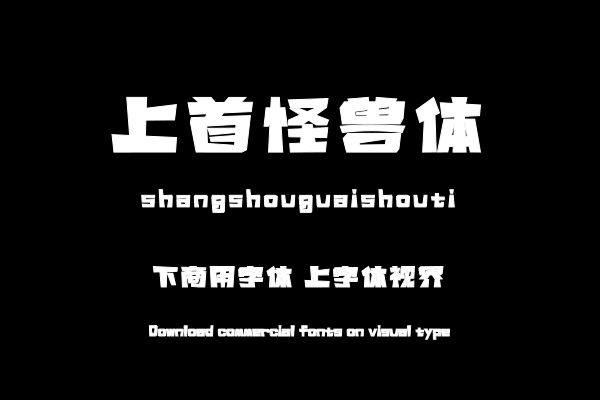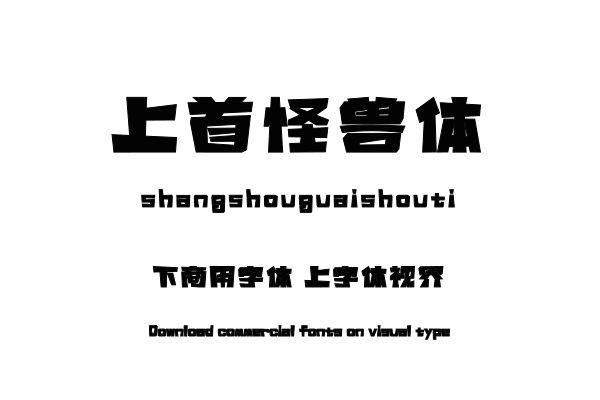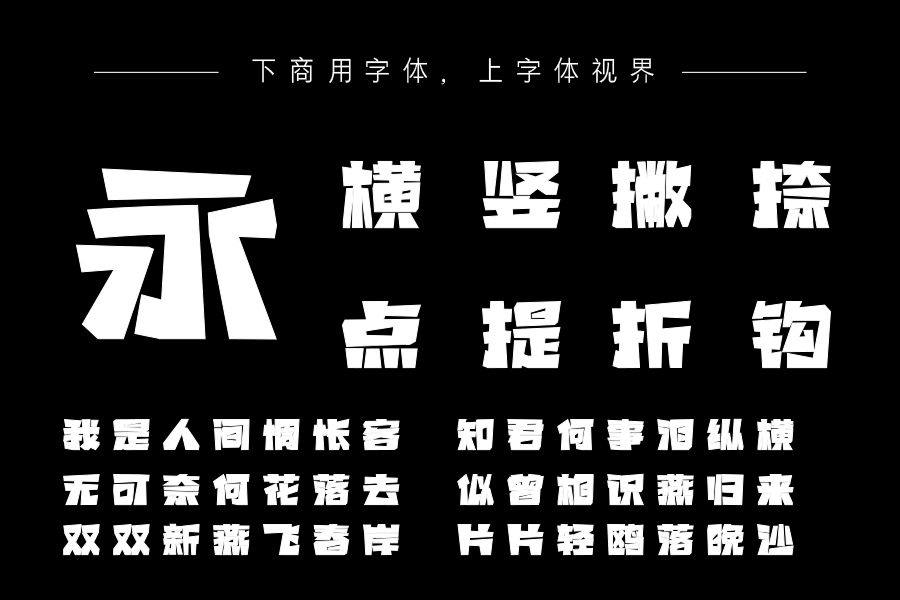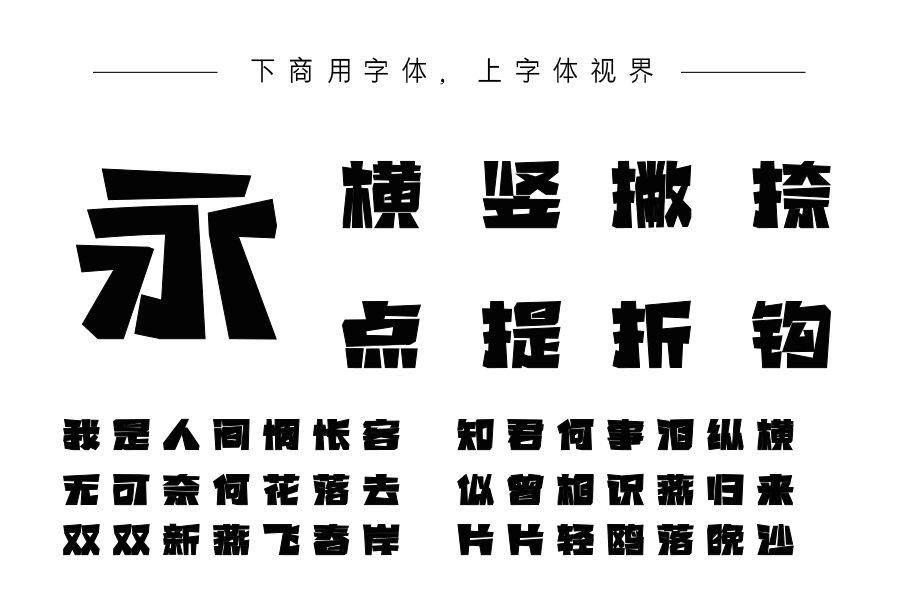
上首怪兽体,整套字以沉稳厚重为主,在字体原有的笔画上进行了梯形外观调整,每个字的笔画都跳出了常规的板正状态,使整个字郑重有力的同时又不失俏皮的感觉,让其更具有现......购买须知:“下载服务费”与“字体VIP”所获得字体 仅用于个人非商用, 商用请联系付费授权。本字体为电脑用字,手机没有root权限不支持直接手机换字(手机如何root,请自行百度搜索教程)。购买前请先 了解清楚后再付款 ,字体为虚拟产品无法回收 一旦购买不支持退款。